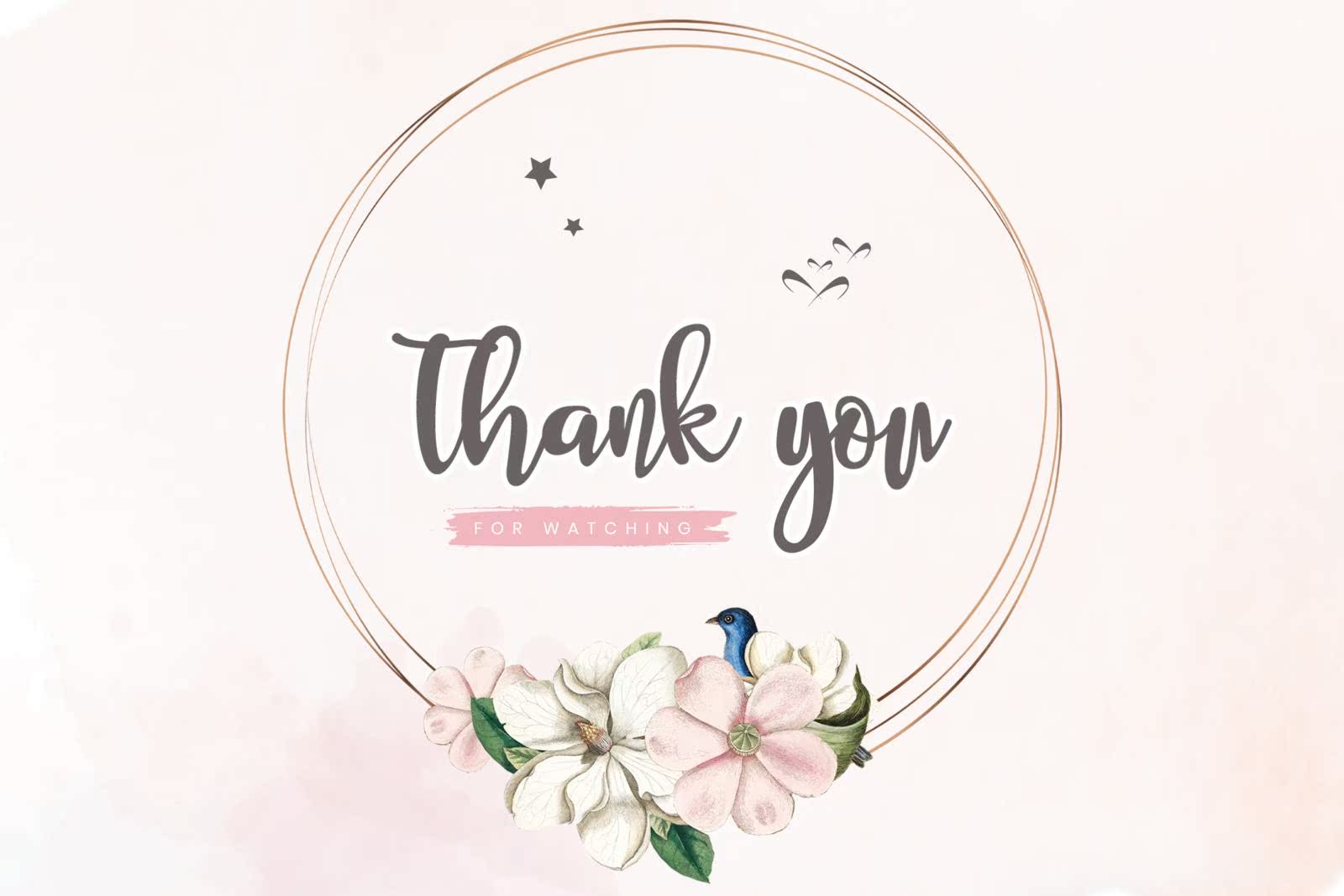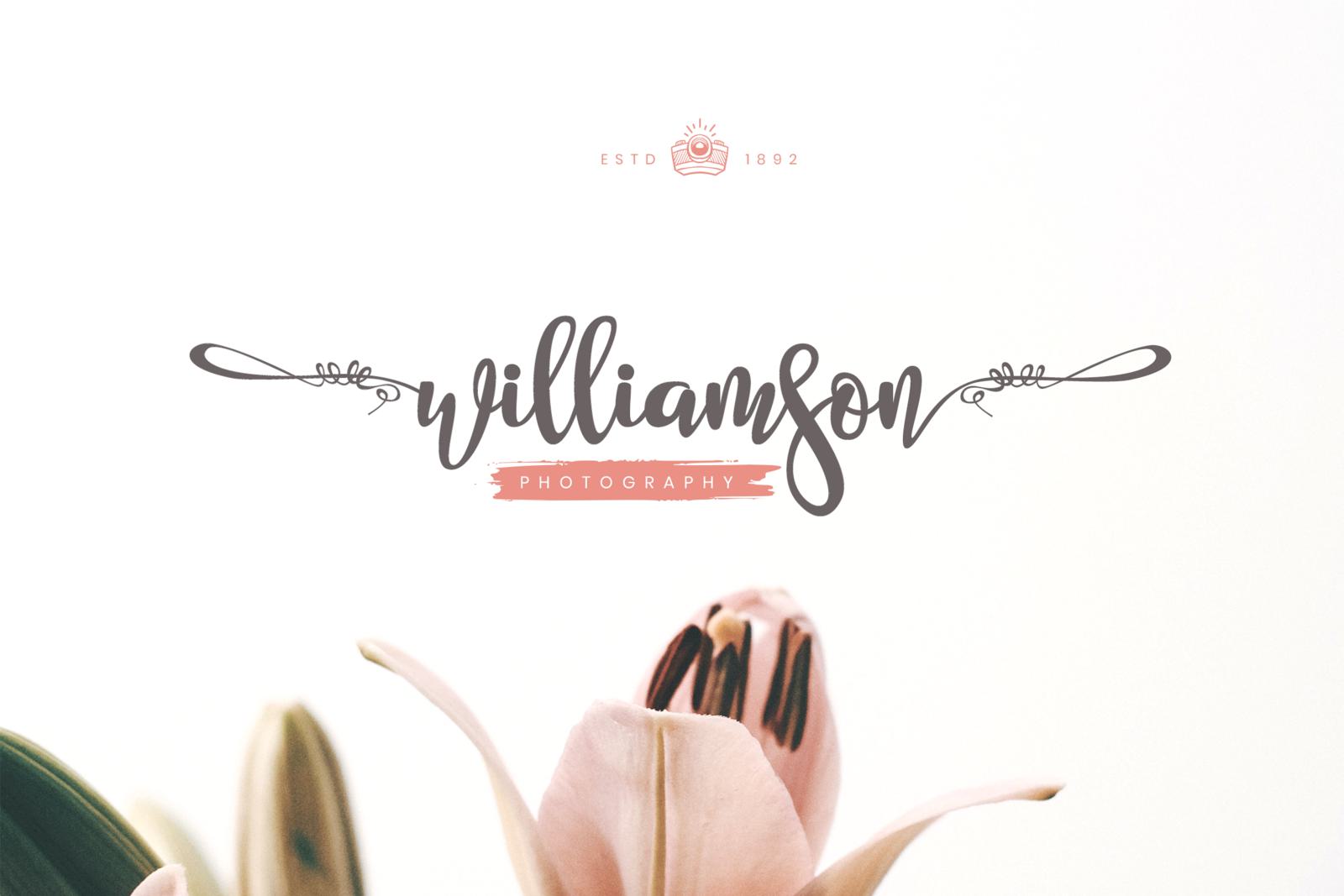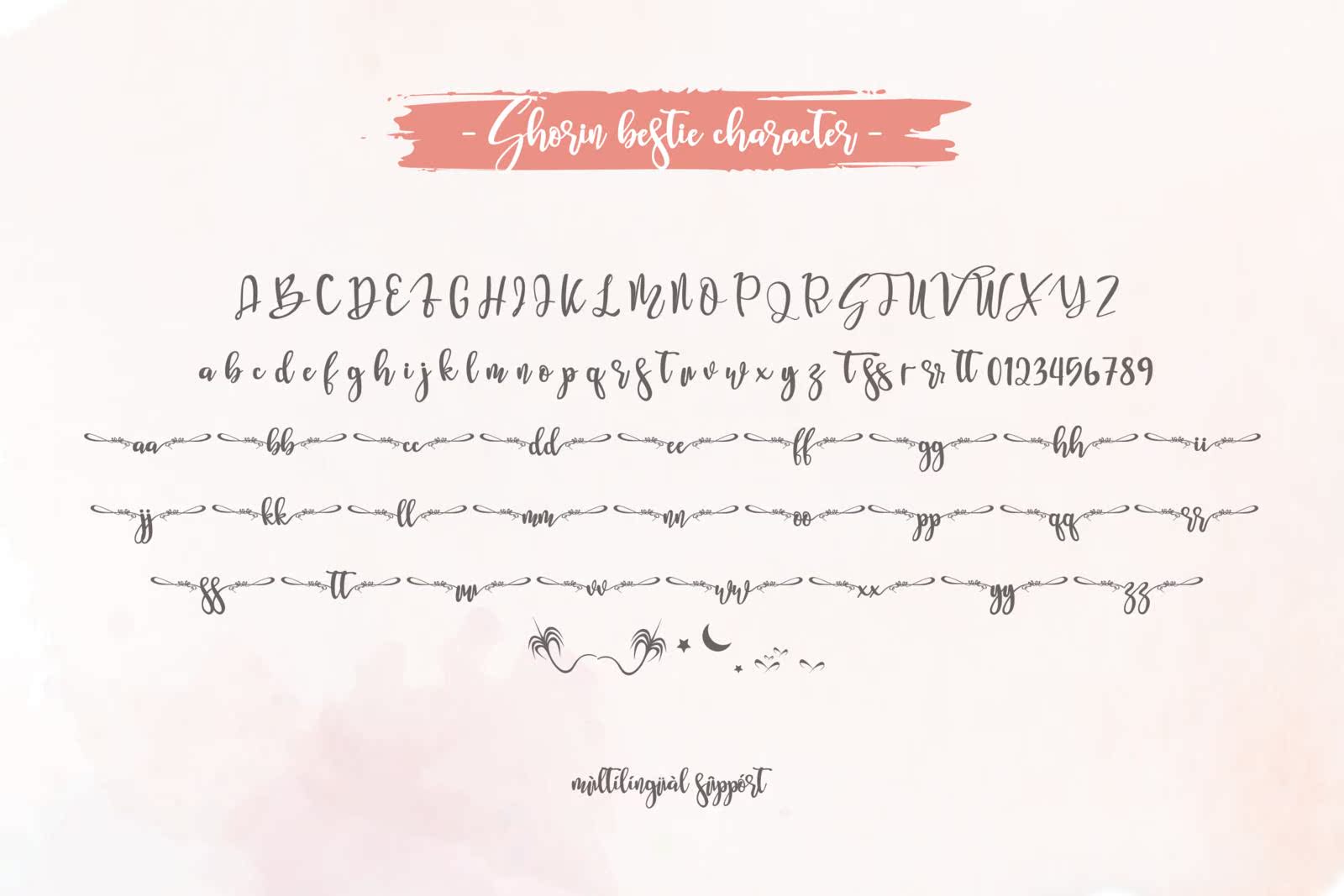
Charming和WritenScriptFontwithPuaEncoded,这意味着您可以访问此Glyph Swithease!它的特点是具有开始和结束的标志和独特的符号。它在婚礼上令人震惊,包括活力卡、感谢卡、报价、问候卡、徽标、名片以及任何其他需要书写和触摸的设计。它以其令人难以置信的独特和永恒的风格深受欢迎,并将其用于壮观的设计!Charming和WritenScriptFontwithPuaEncoded,这意味着您可以访问此Glyph Swithease!它的特点是具有开始和结束的标志和独特的符号。它在婚礼上令人震惊,包括活力卡、感谢卡、报价、问候卡、徽标、名片以及任何其他需要书写和触摸的设计。它以其令人难以置信的独特和永恒的风格深受欢迎,并将其用于壮观的设计!